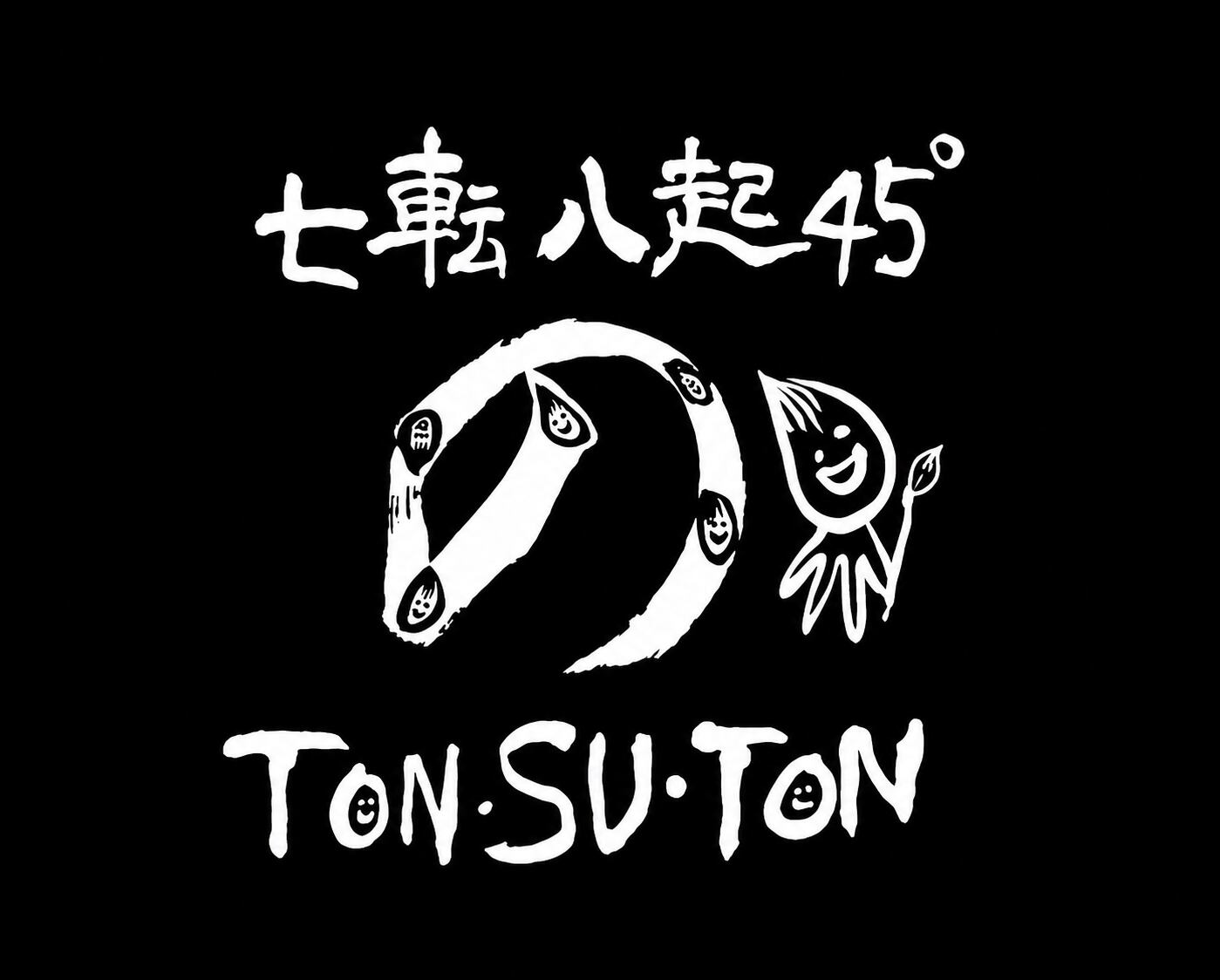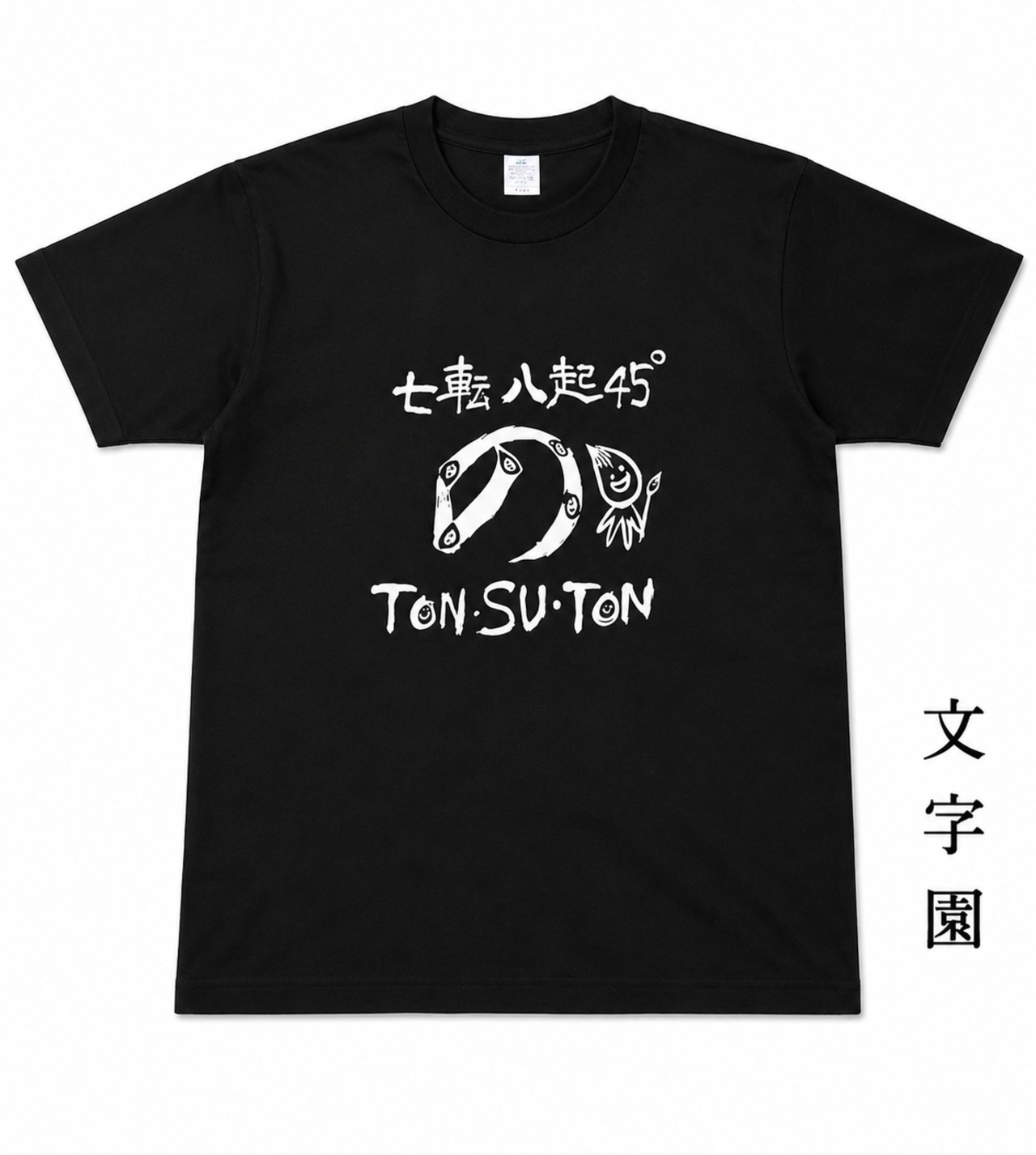
Tシャツ「七転び八起き45°のとんすーとん」
七転び八起き
何があっても起き上がる
ほさきちゃん
穂先(筆の先端)は
転んでも
開かれても
引きずられても
叩かれても
いつだって45°に
立ち上がる♡
筆は獣の毛でつくられています。
自由にさせてくれる
ほさきちゃんに感謝して
仲良くなって
美しい文字を書こう!
指でなぞって遊んでみよう!
触覚で楽しめる!
視覚で学べる!
新しいコミュニケーションを♡
人気者になれるよ♡